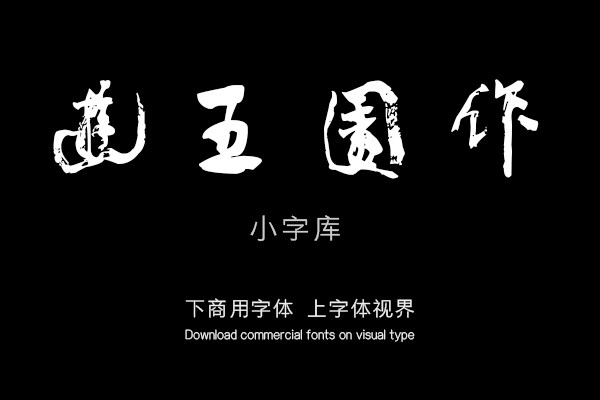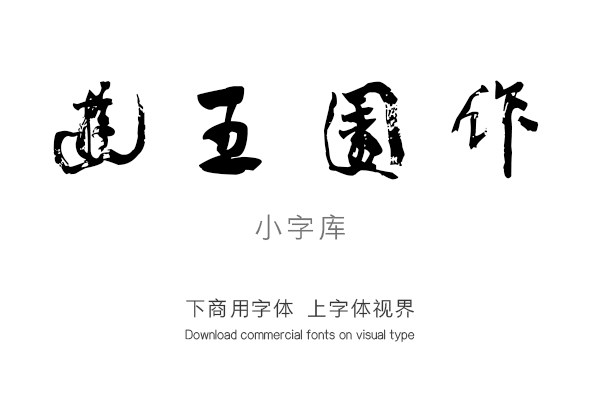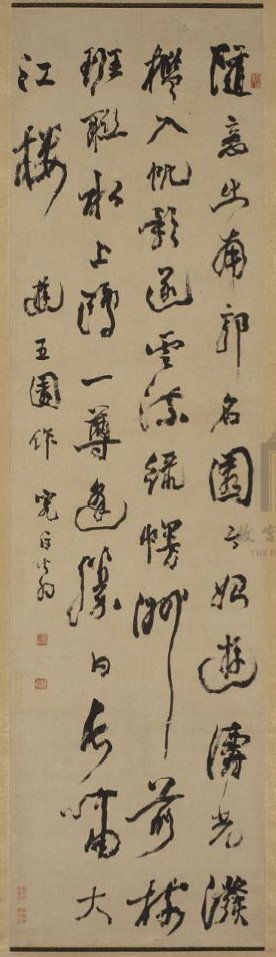
汉标邓琰游五园诗
此轴书法用笔沉实劲健,多有震颤之笔,一波三折,如锥划沙,复存古隶书笔意,体现出邓氏书法兼融古法复自创新的书法特点。邓石如作为清代中期书坛巨擎,其书法不仅诸体悉备......
随意出南郭,名园方始游。涛光泼槛入,帆影逐云流。绿幔洲前楼,班联水上鸥。一尊逢胜日,长啸大江楼。游五园作。完白翁。